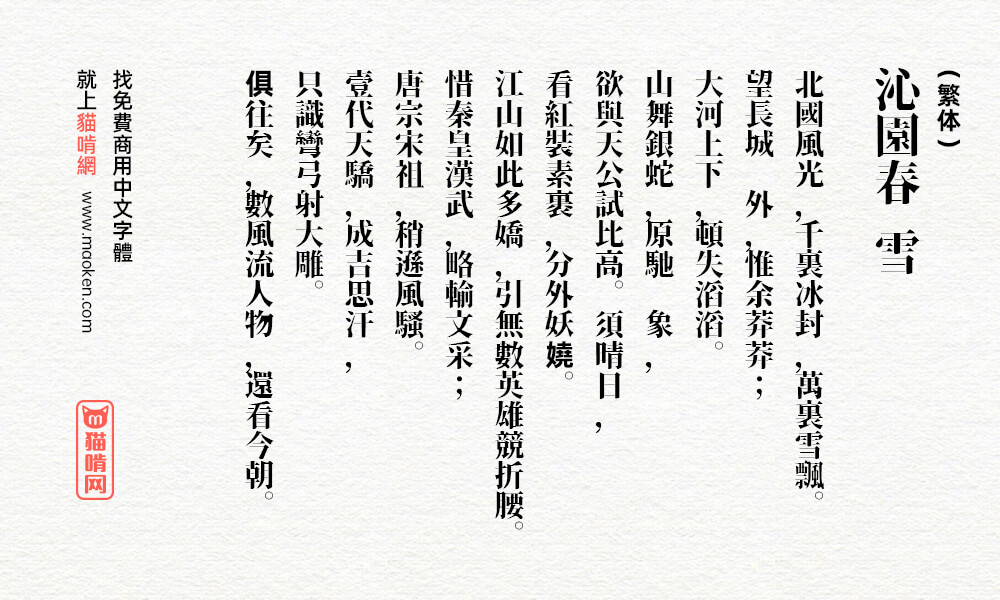
装甲明朝:基于思源宋体修改的免费商用怀旧样式字型
字体作者:浮动设计 (日本) 字体字重:1个
装甲明朝体是一款基于思源宋体修改而成的新字体,可以简单理解成思源宋体的做旧版,出自日本字体爱好者。但因为是日本设计师做的字体,所以对简体中文支持并不是太好,但大多数的常用简体字形还是都有的,如果你发现简体字形在这个字体中无法找到,你可以试试把它转化为繁体字形来试试!
这字体好看,就是简体不齐,哪个大神补补呗
• 不一样吧,他是这思源宋体横变得更细了,还有部分横有断点,变细简单,断点不好做